ブランドイメージを表現するフォント
ブリヂストンは1931年に設立されたタイヤ・ゴム業界におけるグローバルリーディングカンパニーです。コア事業であるタイヤ事業、タイヤ事業の強みを活かしたソリューション事業、免震ゴムやゴルフ用品、自転車等の化工品・多角化事業を展開しています。
ブリヂストンでは、ブランドマニュアルに推奨フォントが設定されていましたが、グローバルで使用が浸透せずブランド表現が統一されていないという課題がありました。そのためデザイン部門では2016年頃からブリヂストンブランドを表現するオリジナルフォントの研究を進め、2020年に新たなブランドアイデンティティを導入するにあたり、ブリヂストンらしさを表現するツールとしてMonotypeの協力のもと欧文書体Bridgestone Typeを開発しました。
「コーポレートフォントの導入の主目的は、社外に対して統一感のあるブリヂストンらしさ、ブランドイメージを表現することにありますが、ブリヂストングループ従業員にも日常業務で使用してもらうことでブランドに対する意識向上、一体感、プライドの醸成といったインターナルブランディング面での効果も意図しています。」とコーポレートブランド部門 BRIDGESTONE DESIGN部 上席研究主幹の酒本康平氏は述べています。
Bridgestone Typeのグローバル展開を進める中で、日本でのブランド表現のためにBridgestone Typeと組み合わせる和文書体の必要性が議論されました。そして、字形のマッチングスコアに加え、サインにも本文にも対応できる汎用性の高さ、コンデンス体を持っている点など和文書体の条件を最も満たす書体としてAXIS Fontが選ばれました。タイププロジェクトは、フィットフォント技術によりBridgestone Typeに合わせてAXIS Font のウエイトを調整し、「BridgestoneType TP」として提供しました。
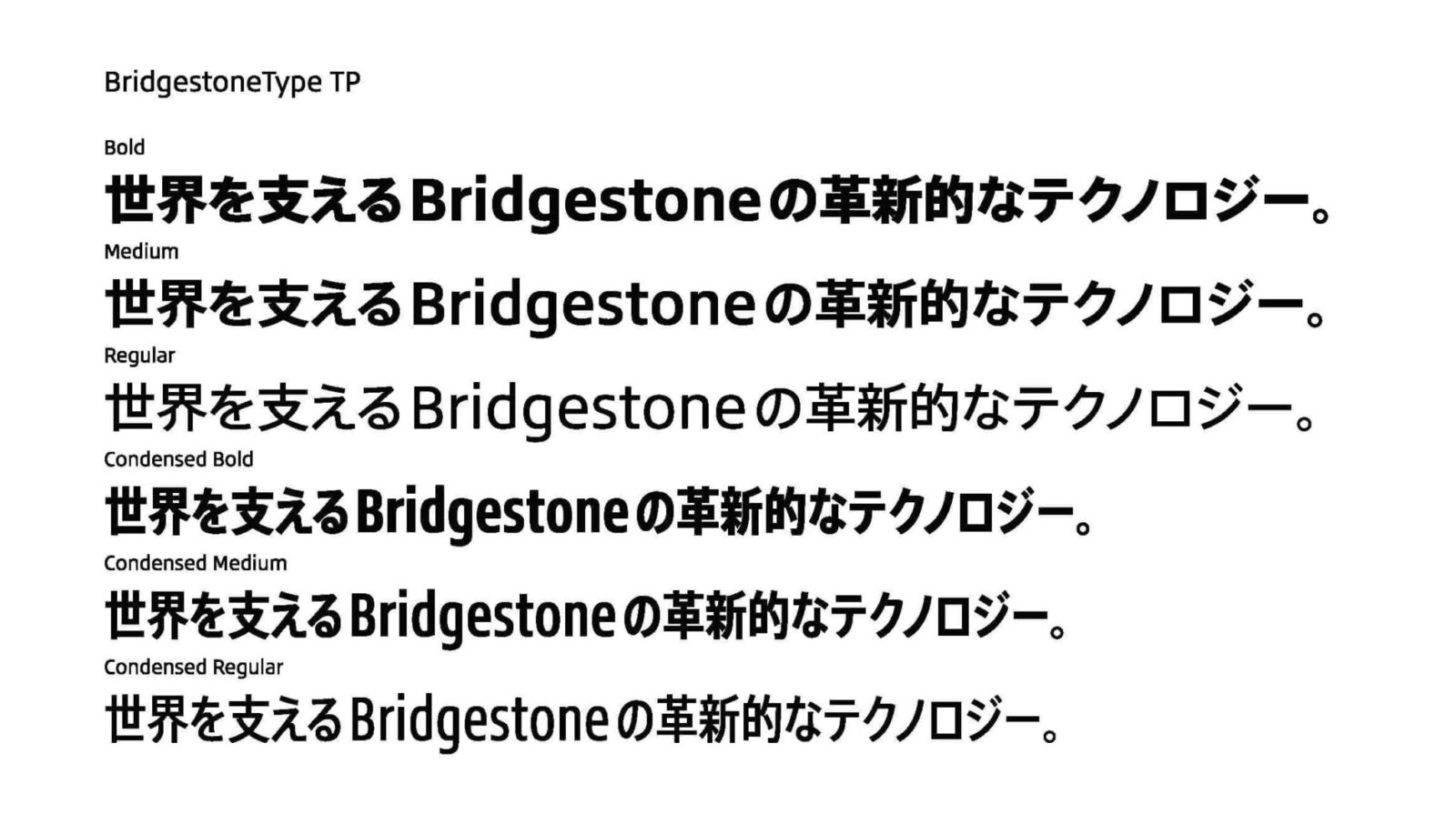
「最終的にはデザイン面での親和性に加え、Webフォントを含む運用面や導入コストなどの点から総合的に判断した結果、AXIS Fontが最適であるとの結論となり採用に至りました。」とコーポレートブランド部門 ブランド管理課の森田明伸氏は語ります。
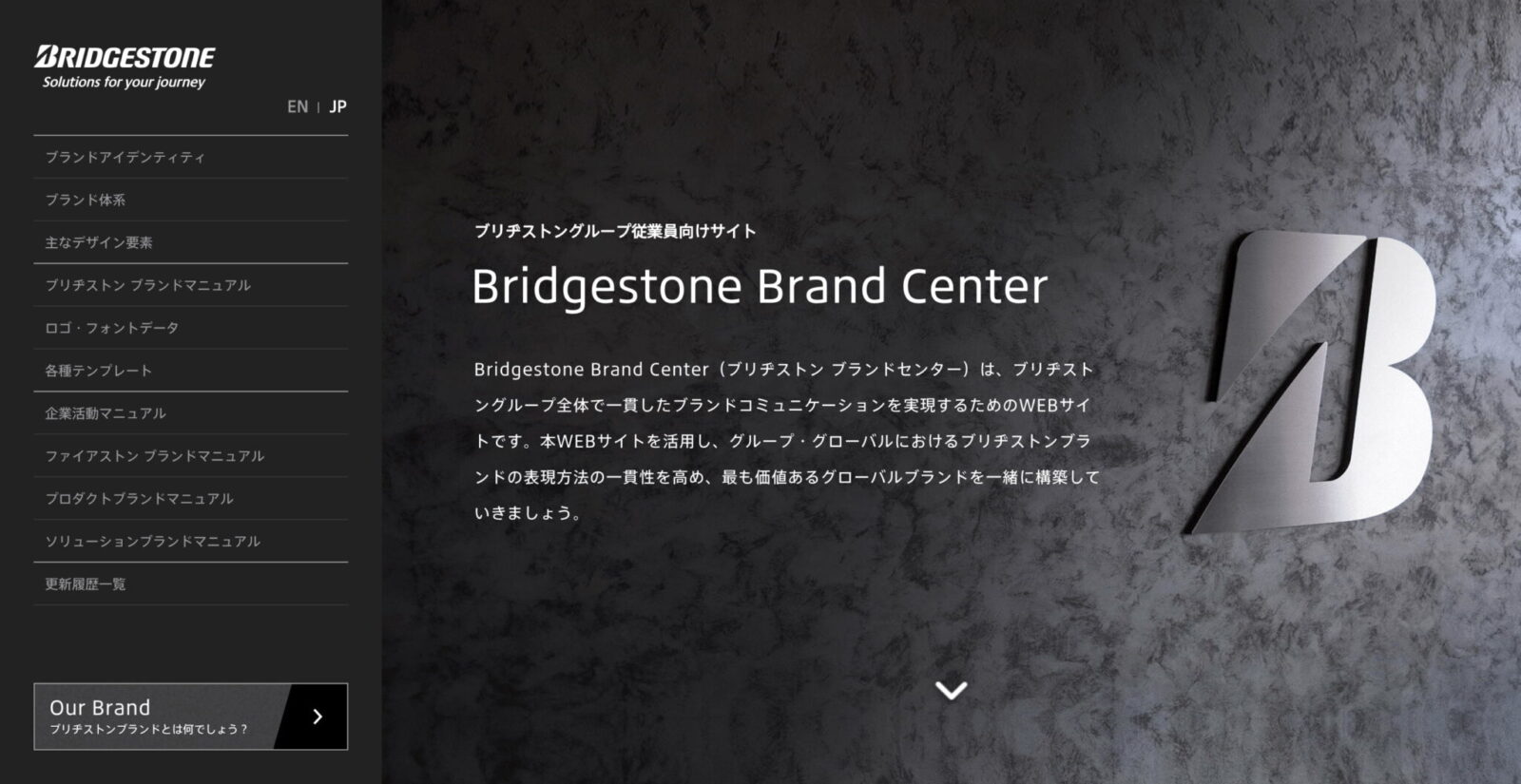
Bridgestone Typeはデザインコードという独自のプロセスでブリヂストンらしさを取り入れており、和文書体においてもこのプロセスによる広範な調査、検証を実施しました。また、検討時にはコーポレートフォントの有用性が関係部門内で認知されているだけでなく、綿密な検証の裏付けもあったため、決定後はスムーズに進んだといいます。
「日本語の場合、欧文書体だけではコーポレートフォントとして完結することは難しく、せっかく作った欧文書体を活かすためには適切な和文書体との組み合わせが必要だと思いました。AXIS Fontの印象はすっきりと洗練されていて、とても現代的な和文書体という印象でした。今回のプロジェクトに当たり、実際にいろいろなテキストを組んで検討してみると、それだけではなく、柔らかさとかやさしさといった雰囲気もある書体であることに気づきました。しっかりとした機能に加えて、人に寄りそうしなやかさを感じさせる点で、ブリヂストンが目指すブランド表現との親和性を感じました。」(酒本氏)
欧文書体のBridgestone Typeは機能性、汎用性、デザイン性について妥協なく追求したコーポレートフォントとして2021年にグッドデザイン賞を受賞しています。和文書体のBridgestoneType TPでもこの特徴が引き継がれており、長期にわたり色あせない普遍性を感じると社外からも評価を得ているといいます。
「社内では既にブリヂストンらしいブランド表現の核として様々なグラフィックデザイン、ロゴや対外発表などに積極的に使われているのもその証左かと思います。」(酒本氏)
「フォント一覧にBridgestoneの名前が出ていることに感動しました。使用した印象としては文字がくっきり、はっきり表示され受け手にとっても読みやすいフォントだと感じました。社内からはどのフォントを使えばよいか明確になったので、資料等作成時にフォント選択を気にする必要がなくなったという声もありました。」(森田氏)
BridgestoneType TPは名刺、封筒などのコーポレートアイテム、施設サイン、広報、広告宣伝、イベント、販促ツール、Webサイト等、さまざまな社外コミュニケーションでの使用が想定されています。
「まだ途上ではありますが、印刷物のような本文、Webサイトからサインシステムまで一貫性のあるブランド表現が実現してきていると思います。さらに、グローバル、関係会社においてもブランドの声を統一できることは非常に大きな成果だと感じます。」(酒本氏)
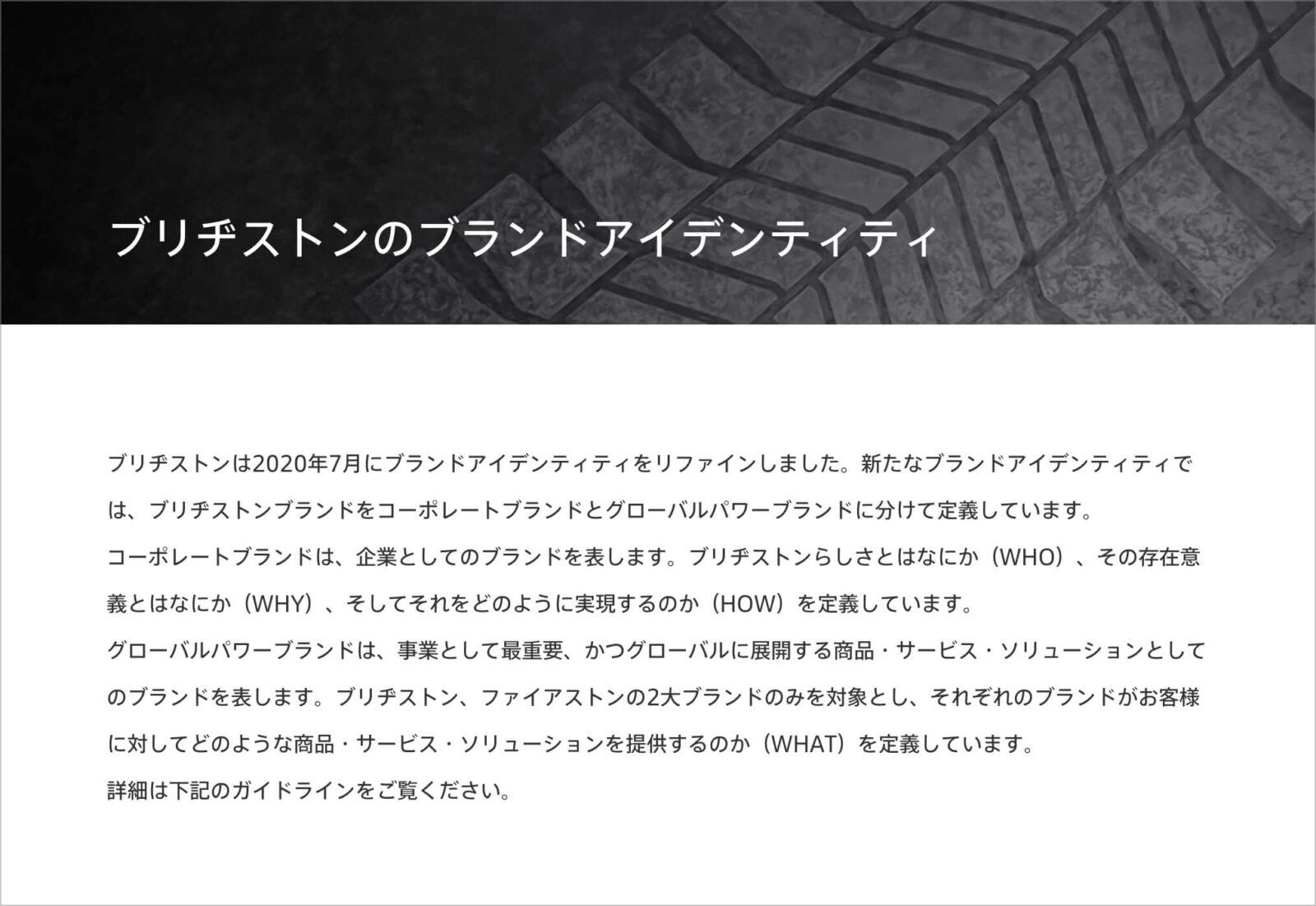
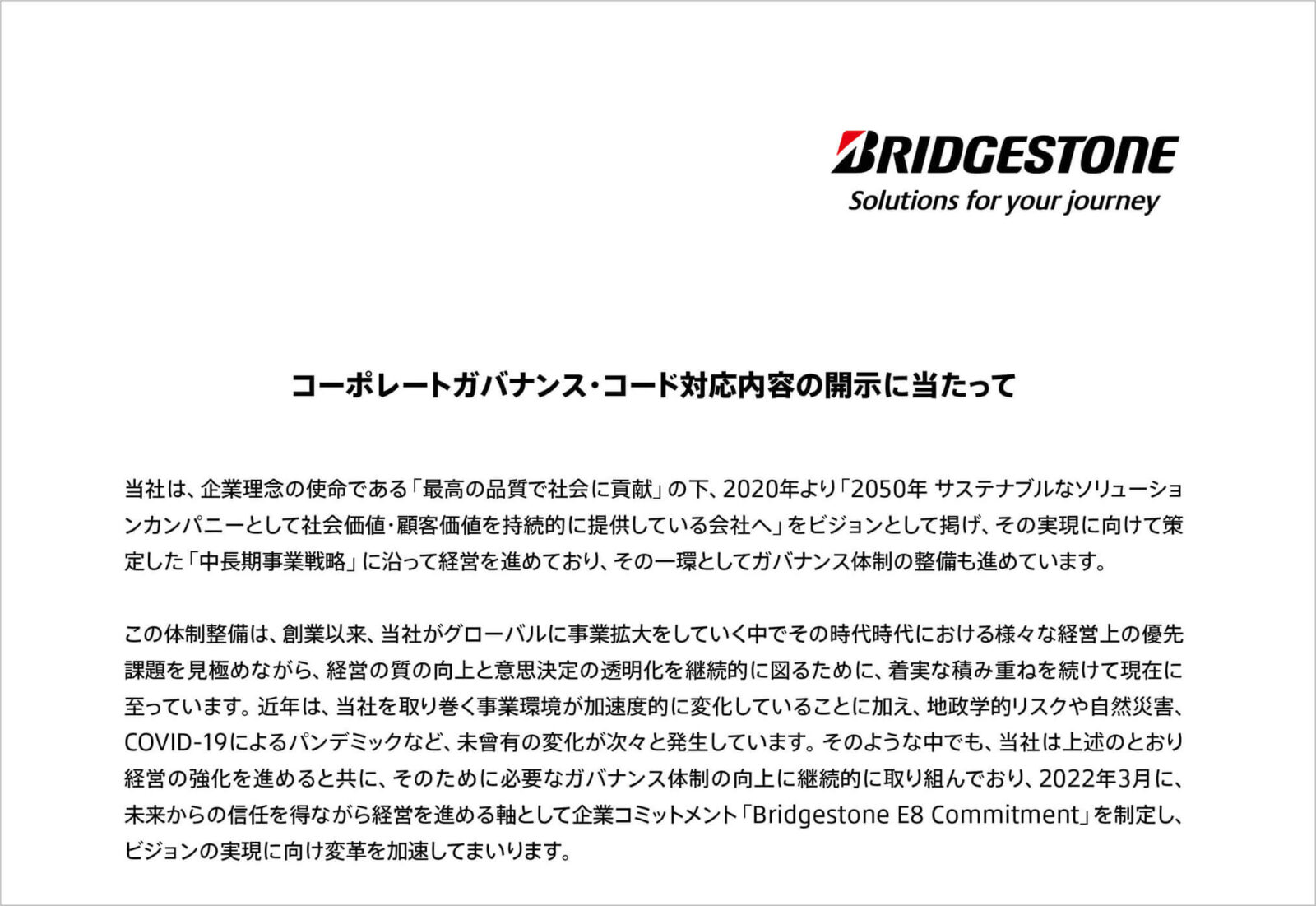
ブリヂストンでは、ブリヂストンらしいブランド表現と共にREGNOやPOTENZAといったプロダクトブランドらしい世界観の表現についても重要だと考えています。コーポレートフォントをブランドコミュニケーションの中心に持つことにより、ブランド表現の一貫性に加え、それぞれのプロダクトブランドらしい表現が活きる好循環が生まれることを期待しているといいます。
「今回のプロジェクトを通じ、ブランド表現やメッセージの統一という点で、フォントは非常に強力なツールだと感じています。また、オリジナルフォントがあることでグローバルを含めた社内のメンバーや部門の連携がスムーズになり、ブランド意識が高まるといった効果も感じています。」(酒本)
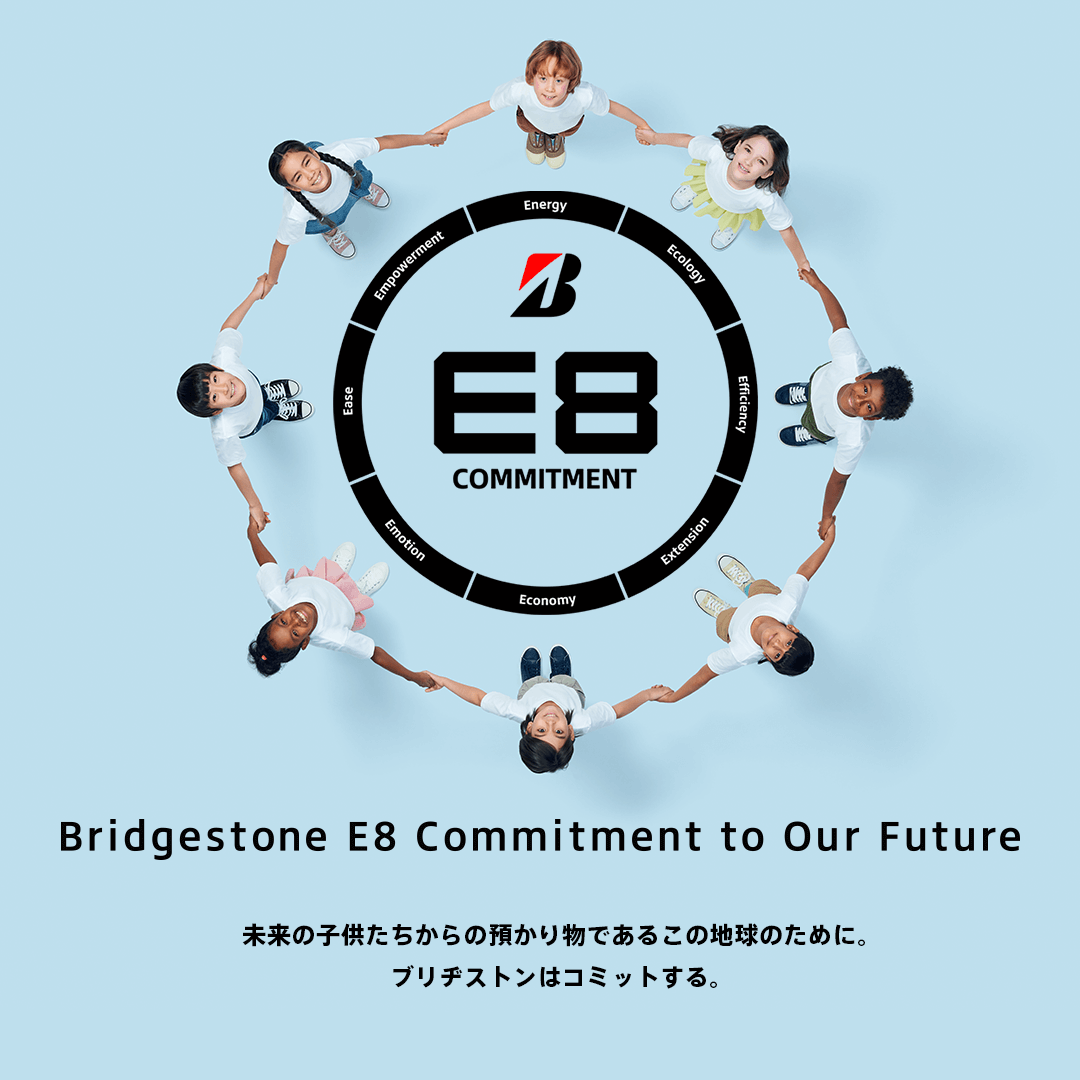
ブリヂストンは、「2050年 サステナブルなソリューションカンパニーとして社会価値・顧客価値を持続的に提供している会社へ」というビジョンの実現に向けて、2022年3月に、Eで始まる8つの価値(Energy、Ecology、Efficiency、Extension、Economy、Emotion、Ease、Empowerment)を定めた企業コミットメント「Bridgestone E8 Commitment」を制定しました。
「Bridgestone E8 Commitmentは、ブリヂストンらしい目的と手段で、従業員や社会、パートナー、そしてお客様と共に創出し、持続可能な社会を支えることにコミットしていくというものです。共創の実現には、ステークホルダーの皆さまから信頼されるブランドであり続けることが大切です。ブランド・デザインの立場から信頼されるブランドの醸成に努めたいと思います。」(森田氏)